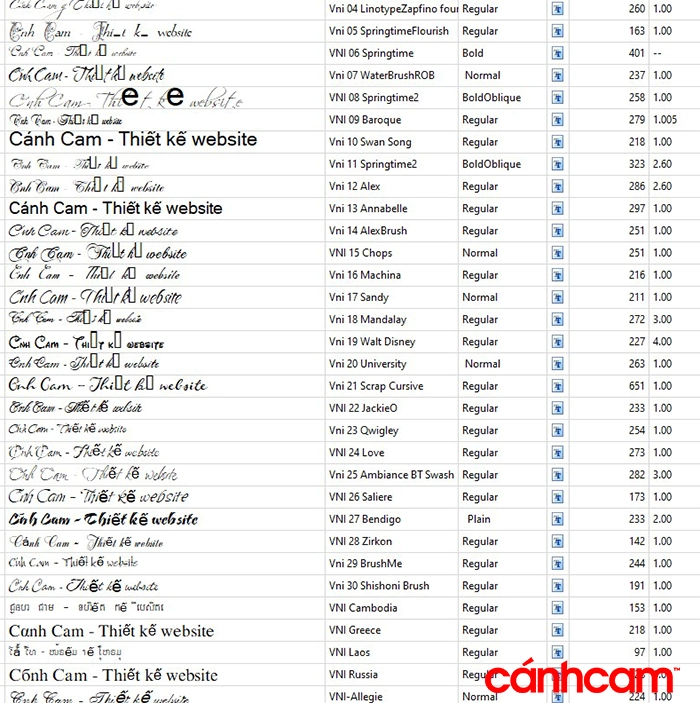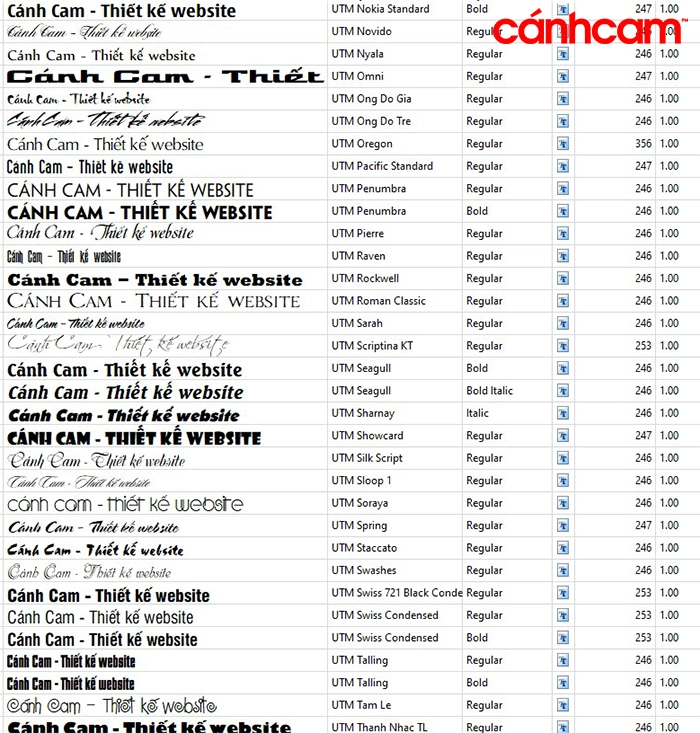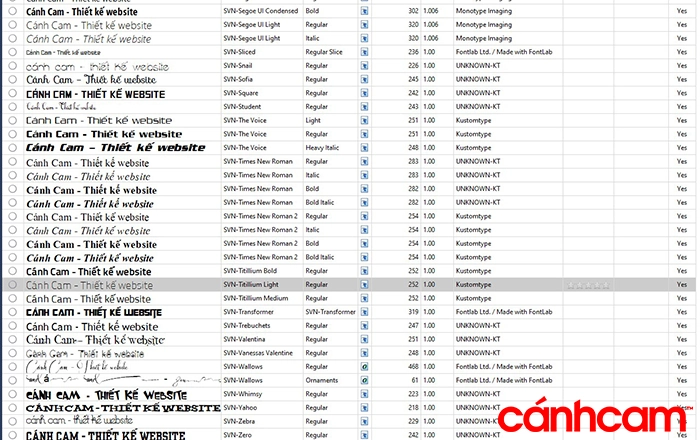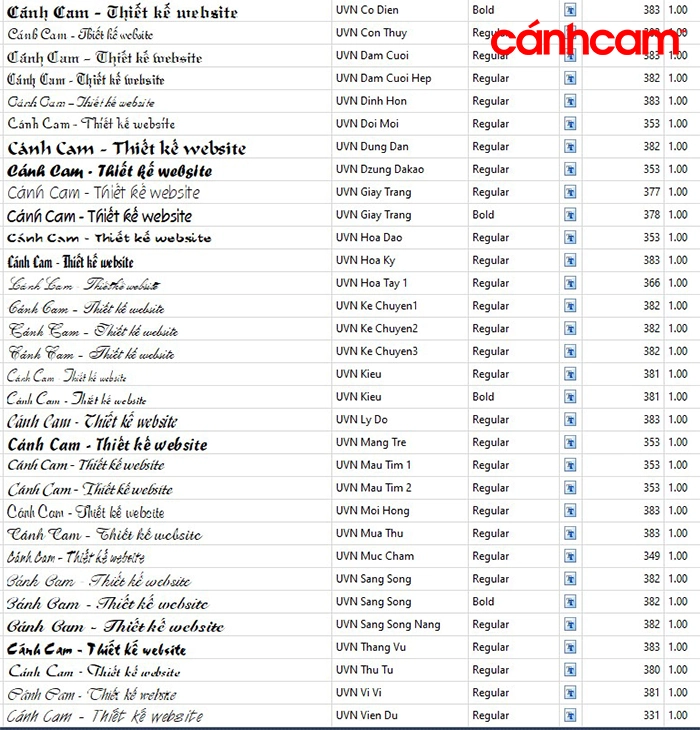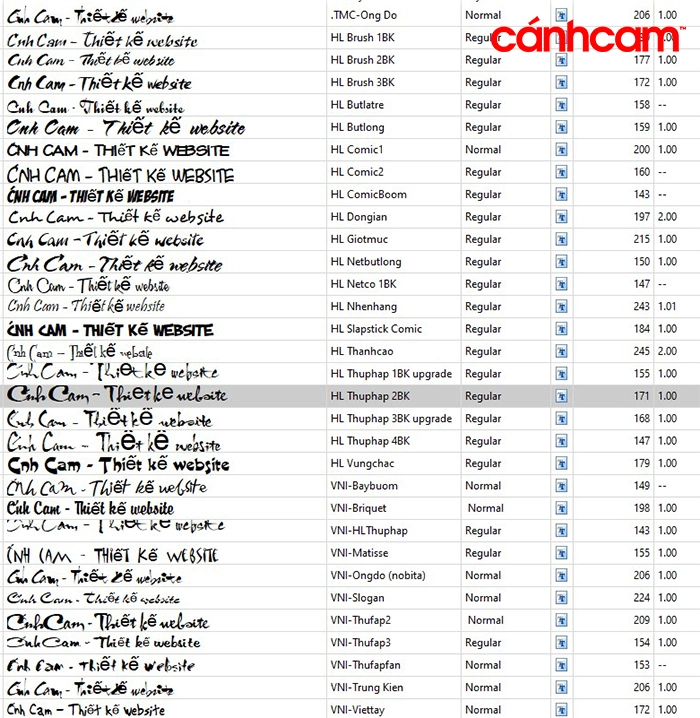
Tổng hợp hơn 1100 font chữ đẹp : font VNI, font UTM, font SVN, font UVN, font Calligraphy, font Viết tay, font Thư pháp và tất cả đều là font chữ Việt hóa sử dụng bảng mã chuẩn quốc tế Unicode. Bộ phông chữ đẹp đa dạng đáp ứng cho mọi nhu cầu : soạn thảo văn bản, thiết kế website, thiết kế đồ họa chuyên nghiệp …
453 Full trọn bộ font chữ VNI đẹp Việt hóa
Đây là font chữ đẹp VNI đầy đủ nhất, bao gồm những font chữ cơ bản dành cho máy tính của bạn đến những font chữ kiểu cách, thư pháp cực đẹp, và font bay bướm, uốn lượn dành cho thiết kế đồ họa.
196 Font chữ UTM Việt hóa
Font UTM hay còn gọi là font Unicode Thiên Minh, đây là font chữ tiếng Việt khá nổi tiếng và được ưu chuộng của người thiết kế, với nhiều font mềm mại, uyển chuyển.
139 Font SVN Việt hóa
Bộ font chữ hỗ trở bảng mã Unicode được Việt Hóa vào nằm 2013 bởi 1 designer được giới thiết kế rất ưu chuộng. Các font chữ nổi tiếng như : font SVN-The Carpenter, Font SVN Wallows, font SVN- Gotham, font SVN-Androgyne, font SVN-Dancing script
214 Font chữ UVN Việt hóa tuyệt đẹp
Trọn bộ 214 font chữ UVN Việt hóa cực đẹp miễn phí, bộ font chữ được Việt hóa bởi tác giả Tom Truong khoảng năm 2011 trên website font nổi tiếng, do font dùng bảng mã chuẩn quốc tế Unicode nên không lo lỗi thời.
Bộ font UVN bao gồm các kiểu chữ mềm mại, uốn lượn, bay bướm : Font UVN Ai Cap, Font UVN Anh Hai, Font UVN Hai Ba Trung, font UVN Bach Dang, font UVN Nguyen Du, font UVN Lac Long Quan, Font UVN Bay Buom, Font UVN Banh Mi …
46 Font chữ thư pháp nghệ thuật
Trong bộ font chữ VNI đã bao gồm hơn 30 font chữ thư pháp các loại, nay bộ sung thêm 46 font chữ sưu tầm khác để đa dạng hóa lựa chọn.
Bộ sưu tập 57 font chữ Calligraphy, font viết tay Việt hóa cực đẹp
Bộ sưu tầm các font chữ Calligraphy, viết tay cực đẹp gồm như: font Madelican Calligraphy, Font Aphrodite Slim, font Everything Calligraphy, font Anjani Script Modern Calligraphy, Font Qwigley Regular, Font Allura, Font Good Vibes, Font Dancing Script, Font Cursif, Font Poem Script , font Acronym, font Avenir Next, font Desire, font Sophia, font Walkway…